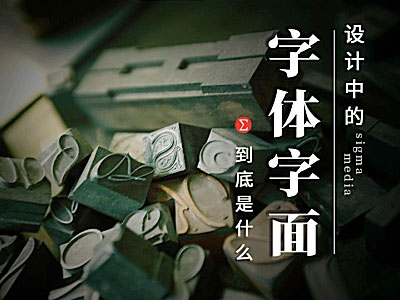
字面到底是什么?曝光字体设计中那些鲜为人知的细节!
你有没有发现:字号相同的几种字体,有的字体看起来大有的字体却看起来小.。
在设计字的时候也常有这样的困惑,明明长宽高都一样,几个字却很难搭在一起,总感觉大小不一。
调整半天还是视觉不统一分分钟摔键盘!不要鸡冻,明白字体设计中的字面概念后你就什么都明白了!
壹—字面不是字很要面子
人类都是要面子的存在,成年人之间的默契就是充分照顾到对方的面子,这以后才有得玩。但我们这里所说的字面,并不是这个很抽象的意思。
这里的“面”单纯而直接,通俗来理解就是指外表,我们设计字时常会以两个方形框作参考来限定字的外表,即字身框和字面框。
而字面就是指字体所占字面框的字面率比例大小。
也就是说,在字面框不变的情况下,把字体设计的外表大就称字面大,外表小则称字面小。这就是同样字号的字,有的字体看起来大而有的字体看起来小的一个重要原因。
字身和字面的概念来自金属活字type face,在金属活字上,字面部分就是凸起的字,铅模外框则是自身。对的,现在字体设计中的自身框、字面框正是由这里演化而来。
因为字身框是不会印出来的,所以字身框又叫做假想框。等等,既然字身框并不会印刷出来,那它存在有什么意义?
单独从一个字来看,字身框确实没多大意义,但金属活字是要排列好铅模后印刷的,而铅模字身的尺寸是固定的,这时候,字面的大小就会影响到字之间的距离了哎呦喂!
也就是说,自身框和字面框共同影响到字距。这也就是在字体设计中,字身框和字面框之间的差值距离是半个自然字距的原因!
So,在设计字时,没必要纠结字身框或字面框本身的大小,而更多的关注他们之间的比例。
贰—你看到的字面不是真正的字面
说的好像逗人玩一样,不要撇嘴,从刚刚对字面的介绍中不难理解,字面是实际可测量的。
字体设计大师谢培元老师总结的“第二中心线”理论也表明,只要测量形旁和声旁这两个部件的中心距离就可以得到相应的字面大小值。
第二中心线理论:适用于形声组合的汉字,取形旁和声旁这两个部件各自的竖直中心线,测量这两条中心线间的距离,距离越大,字面就越大,反之,字面就越小。
那么,单纯如你,设计字体时是不是机械的把所有字的字面都精准统一?难道不应该这样吗?这样做初衷是对的,但效果往往是让人摔键盘的。
别问为什么,因为汉字极其复杂,有的笔画多有的笔画少,外形轮廓也是千姿百态,如果机械的精准统一可测量的字面,结果往往有的字看起来大有的字看起来小,视觉上的字面并不统一!
视觉效果和几何效果就是这么折磨人!所以说在设计中正确处理字面,是要做到统一视觉字面,而不是可测量的字面。
如果把字面形状按照视觉习惯归类为规则的几何图形,我们可以大致把汉字归纳为方形、圆形、三角形和菱形4种典型形状,针对这四种类型作相应处理,就能做到字体在视觉上字面保持一致。
方形和圆形横竖延伸刚很强,视觉上会膨胀所以要适当缩短笔画,不要占满字面框;菱形收缩感很强,边角要靠近字面框扩大视觉面积,而三角形的底边远离字面框,才能达到字面的统一。
关于字面现在了解的一清二楚了吧?字面框、自身框、第二中心线、视觉字面以及字面概念的来源都掌握了,字体设计进阶指日可待!